4个标准黑体字体下载优质网站推荐,新手也能快速下载使用
做电商主图时,想用醒目的黑体突出产品卖点,翻遍文件夹却只有模糊的旧字体?写工作总结时,觉得默认字体太过平淡,想换款专业黑体却担心下载到带病毒的文件?运营公众号排版,精心挑选的标题因为字体版权问题,刚发布就被平台警告?相信不少新手在设计、办公或内容创作时,都曾被“找字体”这件看似简单的事绊住脚。
要么是下载的黑体字体发虚、有锯齿,放大后完全没法用;要么是分不清“个人使用”和“商用”的界限,一不小心就踩了版权雷区;更有甚者,点进所谓的“免费字体网”,满屏广告弹窗不说,下载的文件还根本不是字体格式。其实,标准黑体字体的下载没那么复杂,关键是找对靠谱的平台。今天就为大家整理4个亲测优质的字体网站,操作简单到新手一看就会,3分钟就能搞定你的字体需求,彻底告别字体焦虑。
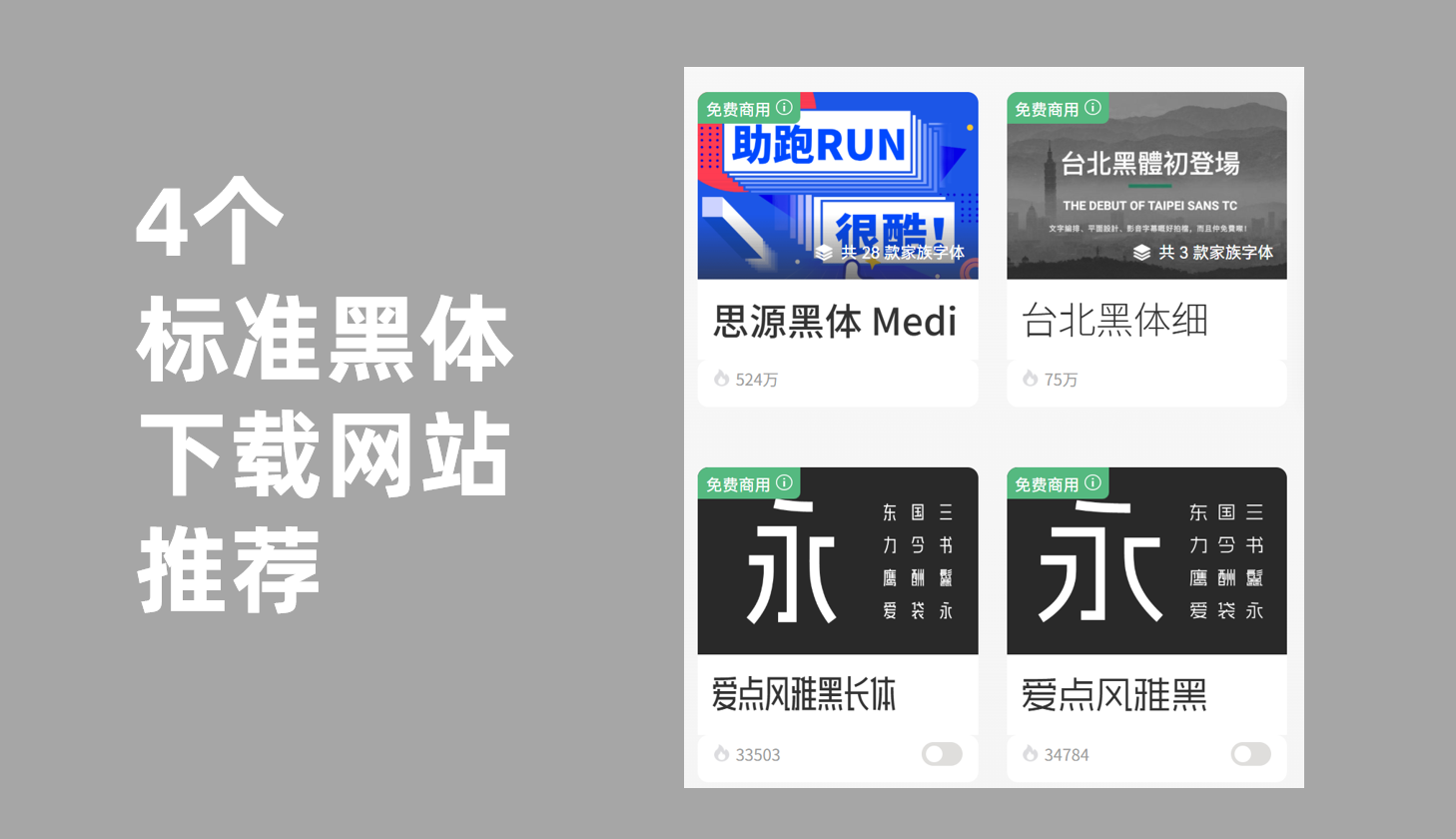
一、字由网
新手友好度拉满的字由网。作为国内知名的字体平台,它最打动我的就是“零门槛”和“高保障”。打开网站后,直接在搜索栏输入“黑体”,就能看到上百种不同风格的标准黑体——从最基础的方正黑体、微软雅黑,到带有设计感的粗体、特黑体,甚至适合商务场景的衬线黑体都一应俱全。
字由网的优势特别突出:一是字体预览功能超直观,点击字体就能看到在不同字号、不同场景下的显示效果,不用下载就能判断是否符合需求;二是版权标注清晰,每款字体都明确标注了“商用免费”“个人免费”或“需授权”,新手再也不用担心不小心侵权;三是下载流程简单,选好字体后点击“下载”,跟着提示一步操作,几秒钟就能保存到本地,还附带安装教程,连电脑小白都能轻松上手。另外它还有客户端,登录后能直接在PS、Word等软件里调用字体,效率更高。
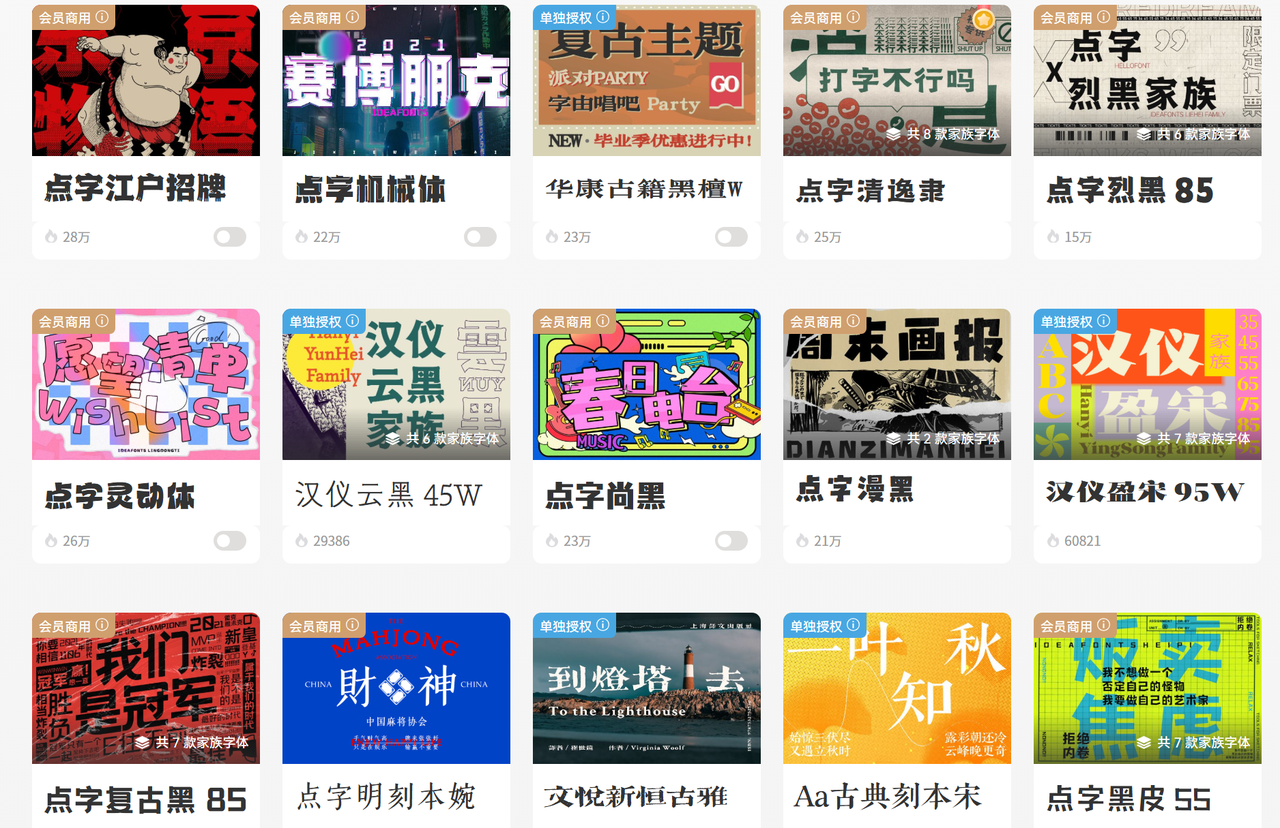
二、字体天下
字体天下,这是个老牌字体网站,主打“全而精”。它的黑体字体分类特别细致,按“常用黑体”“艺术黑体”“手写黑体”等维度划分,如果你需要特殊风格的黑体,比如适合儿童海报的圆润黑体,或是适合科技产品的锐利黑体,在这里都能精准找到。网站的字体文件经过严格审核,下载后解压无广告、无捆绑,安装后在各类软件中都能稳定显示,不会出现乱码问题。新手可以重点关注它的“新手专区”,里面整理了热门黑体字体包,一键下载就能满足大部分基础需求。
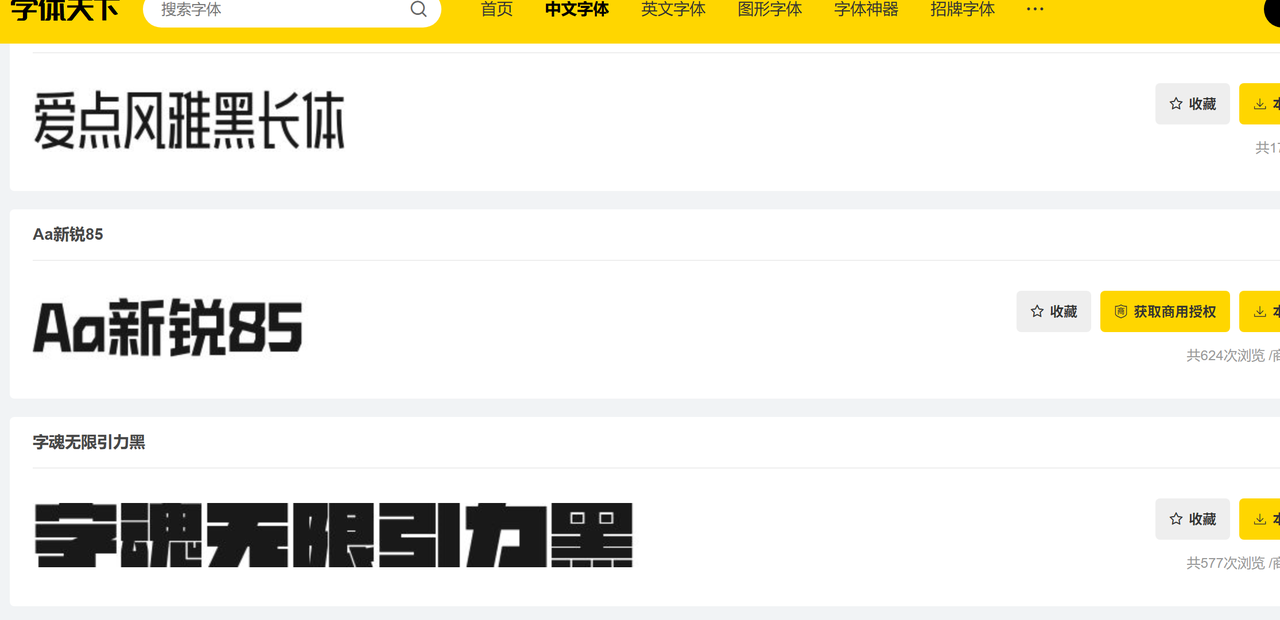
三、100 Font
对于经常做自媒体封面、短视频字幕的新手来说,版权问题是重中之重,100 font直接帮你扫清障碍——所有标注“免费商用”的黑体字体,都经过版权核实,可放心用于商业设计。网站界面简洁无弹窗,搜索“黑体”后,会按下载量排序,排在前面的都是经过大众验证的优质字体,省去你筛选的时间。下载时还会贴心提示字体的适用场景,比如“适合大标题”“适合正文排版”,新手跟着选准没错。
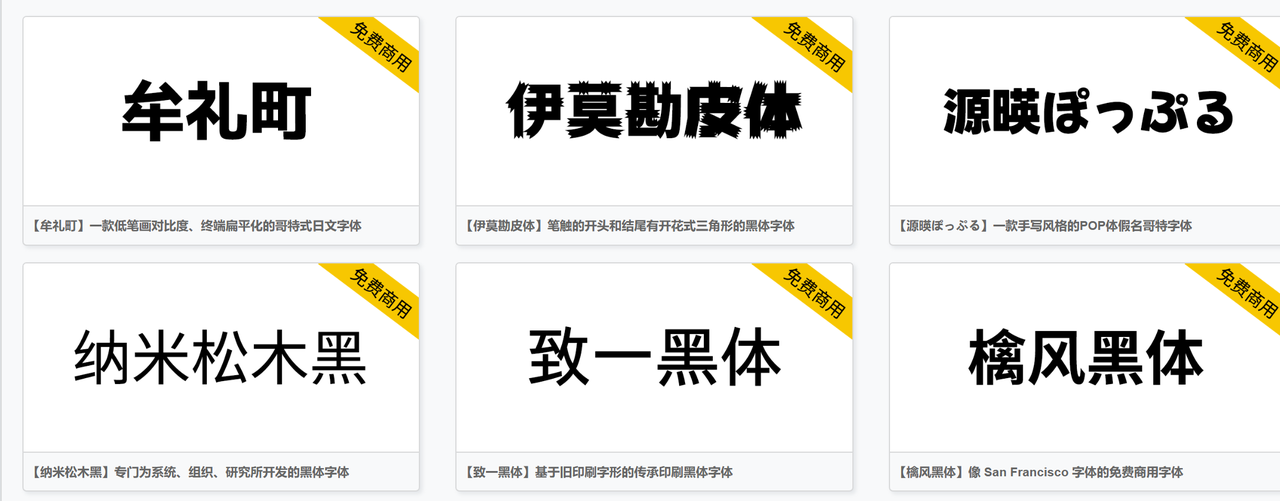
四、站长字体
站长字体是设计师圈公认的“字体宝库”,黑体字体资源丰富且更新快。除了常见的标准黑体,这里还有很多小众但优质的黑体字体,比如带有复古质感的老宋体黑体、融合现代美学的极简黑体,能满足你差异化的设计需求。网站的“字体对比”功能很实用,新手可以同时选中多款黑体,在同一文本下对比显示效果,快速找到最心仪的那一款。下载流程也很简单,无需注册登录,点击下载按钮就能直接获取,还支持在线预览字体的字符集,确保字体包含你需要的生僻字。